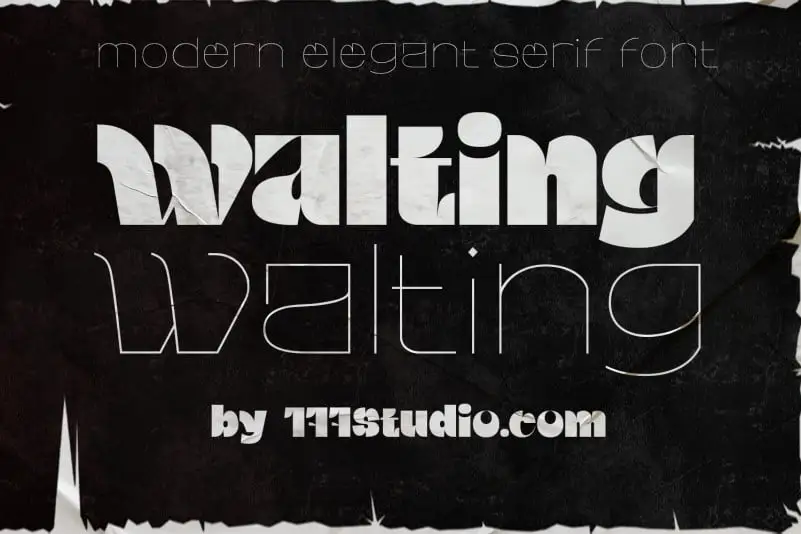
Walting Display Font – Download Grátis
Walting Display Font é uma tipografia sans-serif com impressionantes letras em maiúsculas, projetadas para criar um impacto imediato. Embora se baseie na geometria pura, suas formas expressivas e divertidas garantem que seja perfeitamente adaptável a múltiplas aplicações. Este tipo de fonte é ideal para trabalhos de marca, logotipos, design de casamentos, posts nas redes sociais, anúncios, embalagens de produtos, designs de produtos, etiquetas, fotografia e até mesmo como fundo ou marcas em imagens. Walting Display Font traz uma leveza à tipografia tradicional, tornando-a perfeitamente adequada para um número impressionante de projetos que precisam de uma sensação quase humanizada. Este tipo de fonte é especialmente útil para os designers digitais que buscam aperfeiçoar sua identidade visual e estabelecer uma conexão emocional com o público ao mesmo tempo em que mantêm um toque moderno e despojado.